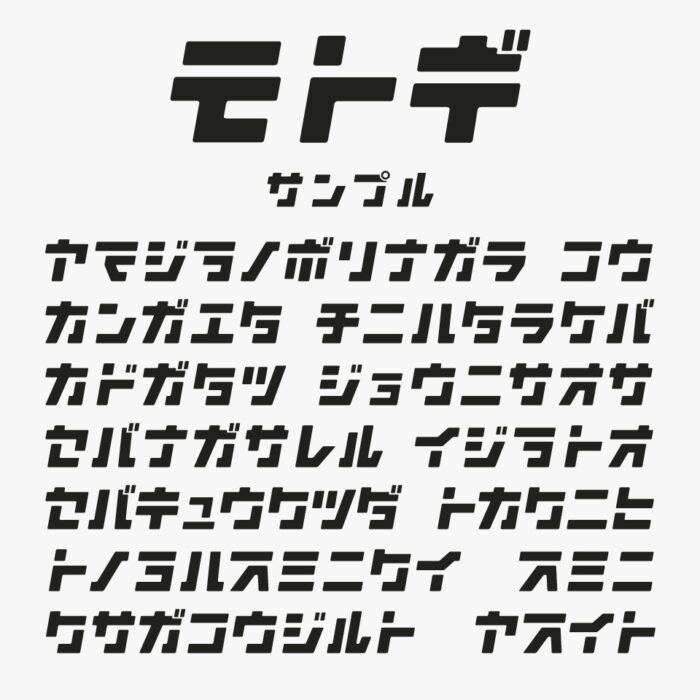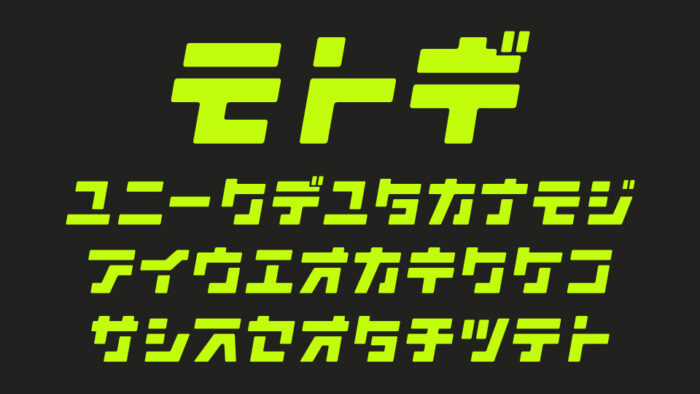
モトギフォントは、どっしりとした台形的な骨格と、丸みを持たないエッジの効いたカットが印象的なカタカナフォントです。
統一されたどっしりとした極太で安定感がありつつも、横に直線的にカットされたエッジがスピード感と力強さを感じさせるデザインです。
スポーツやテクノロジー、工業系のデザインとの相性が良いデザインフォントです。
収録文字は、カタカナ・一部記号が収録されています。